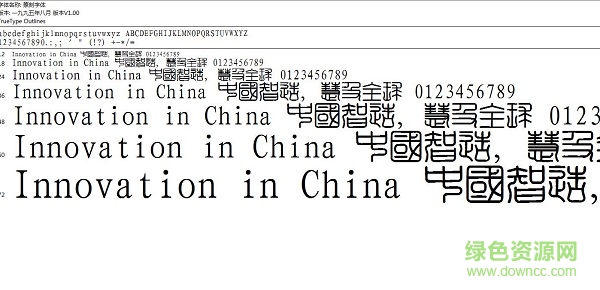
經(jīng)典篆刻字體是一款常見的繁體字體,線條勻凈,字形繁復(fù),雖然不易識(shí)別,但藝術(shù)性較強(qiáng),適合用在影視海報(bào)、牌匾設(shè)計(jì)、古典書籍封面設(shè)計(jì)等方面,喜歡的朋友歡迎免費(fèi)下載!
漢字的古代體之一,它的名字見于漢代著作,與'小篆'對(duì)稱。廣義指'小篆'以前的文字和書體,包括甲骨文、鐘鼎文、籀文和六國(guó)文字等;狹義專指周宣王太史籀厘定的文字,即'籀文'。